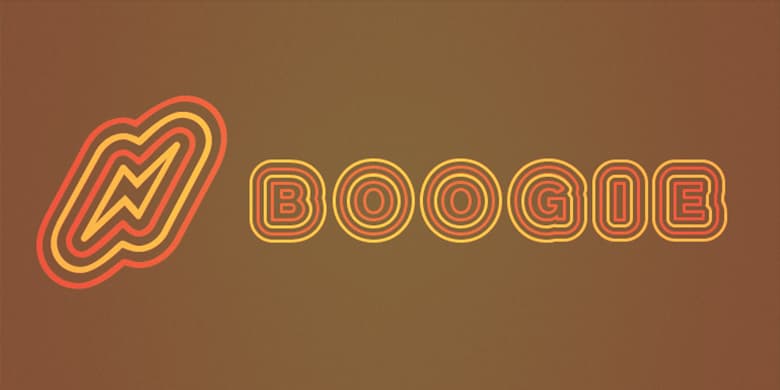
Boogie™
德国平面设计师Ralf Weissmantel在2003年创作了Boogie。Boogie是对波普艺术和20世纪六七十年代迪斯科字体的讽刺。它的圆形形状和轮廓唤起了那个时代闪烁、跳动的灯光和音乐。Boogie字体有五种不同的、宽度兼容的字体,有四个不同的组成部分:一个外轮廓线字形是基本元素,形成第一种字体。另外三种字体可以在这个基础之上分层,用最多三个气泡轮廓包围第一种字体。在adobe photoshop或Illustrator等图形应用程序中,可以为这些元素分配不同的颜色。还有第五种字体,它包含了基础轮廓的字体,被三种相同颜色的额外轮廓所包围。
Boogie在大标题、显示和标识应用中表现最好,在这些应用中,可以清楚地看到和欣赏它的形式。当应用不同的彩色图层时,在Boogie中设置的文本将在页面上旋转并跳动!
Weissmantel曾担任多家国际广告公司的艺术总监,并领导过Grey和MetaDesign等公司的企业设计项目。他的设计作品获得了国际荣誉,被收录在汉堡艺术与贸易博物馆的排印收藏中。他目前在Düsseldorf University of Applied Sciences教授平面设计。Weissmantel自2002年8月以来一直是United Designers Network的合伙人。
在2003年由Linotype GmbH主办的国际字体设计大赛中,Boogie获得了荣誉奖。
German graphic designer Ralf Weissmantel created Boogie in 2003. Boogie is an ironic reference to pop art, and to disco lettering from the 1960s and 70s. Its round forms and outlines evoke the flashing, pulsating lights and music of that era. Shipping with five different, width-compatible fonts, the Boogie typeface has four different components: an outlined letterform is the base element, and forms the first font. Three additional fonts may be layered over top of this base, surrounding the first font with up to three bubble-outlines. In graphics applications like Adobe PhotoShop or Illustrator, these elements can each be assigned different colors. There is also a fifth font, which contains the base outlined letterform pre-surrounded by three additional outlines of the same color.
Boogie works best in large headline, display and signage applications, where its forms can be clearly seen and enjoyed. When different colored layers are applied, text set in Boogie will gyrate and jive across the page!
Weissmantel has worked as an art director for various international advertising agencies, and has led Corporate Design projects for firms such as Grey and MetaDesign. His design work, honored internationally, has been included in the typography collection of the Museum for Art and Trade in Hamburg. He is currently teaching graphic design at the Düsseldorf University of Applied Sciences. Weissmantel has been an associate of the United Designers Network since August 2002.
Boogie received an Honorable Mention in the 2003 International Type Design Contest, sponsored by Linotype GmbH.